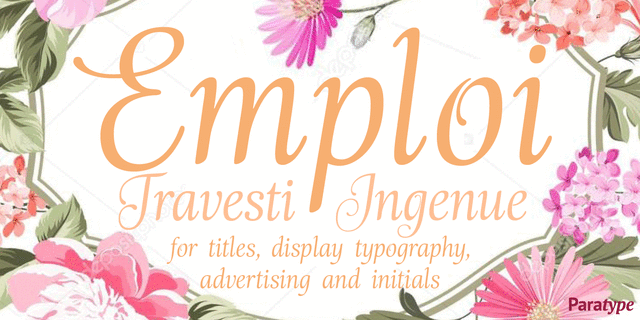
Комплект Амплуа состоит из двух декоративных шрифтов, сочетающих черты регулярного курсива и каллиграфии. Элегантные росчерки и завитки у прописных знаков придают шрифтам нарядность и некоторую театральность, что, в частности, повлияло на выбор названия. Амплуа Инженю имеет более развитые декоративные элементы, Амплуа Травести отличается более сдержанным рисунком. Предназначены для титульного набора и акциденции, в частности рекламы, а также для использования в качестве буквиц. Шрифты разработаны Натальей Васильевой и выпущены компанией ПараТайп в 2009 году.